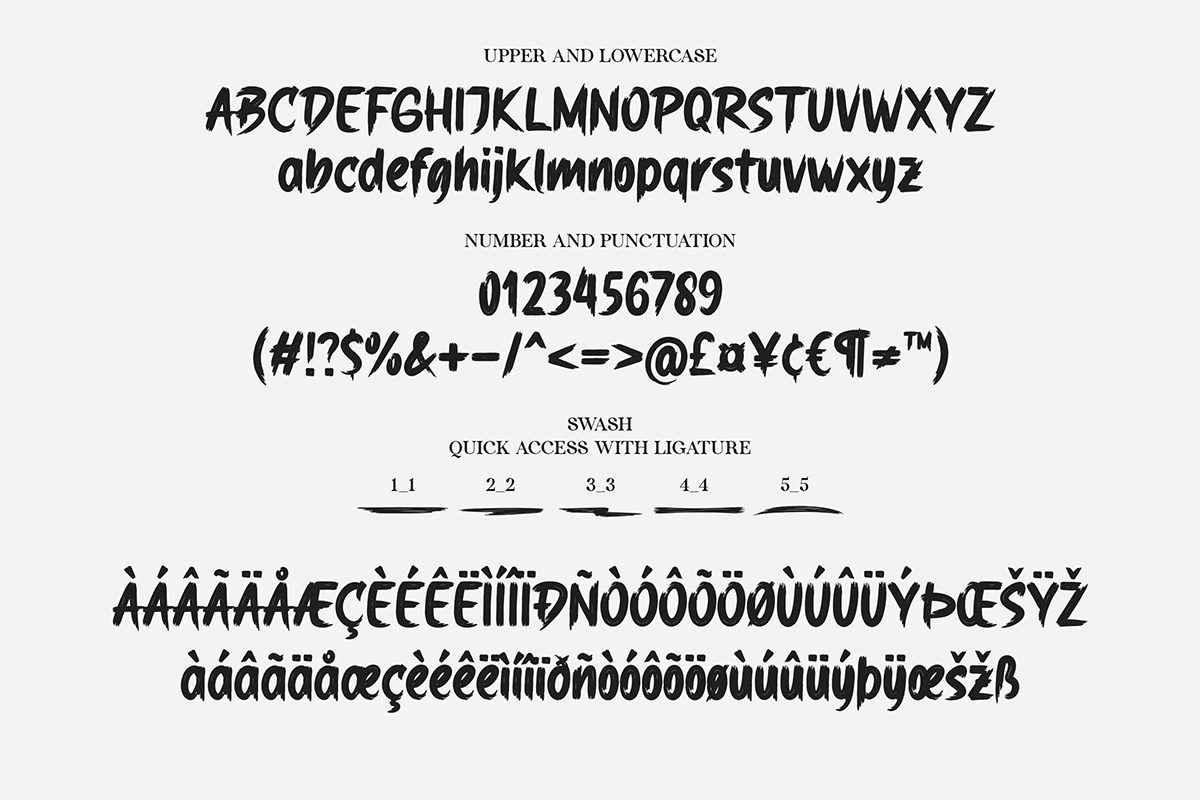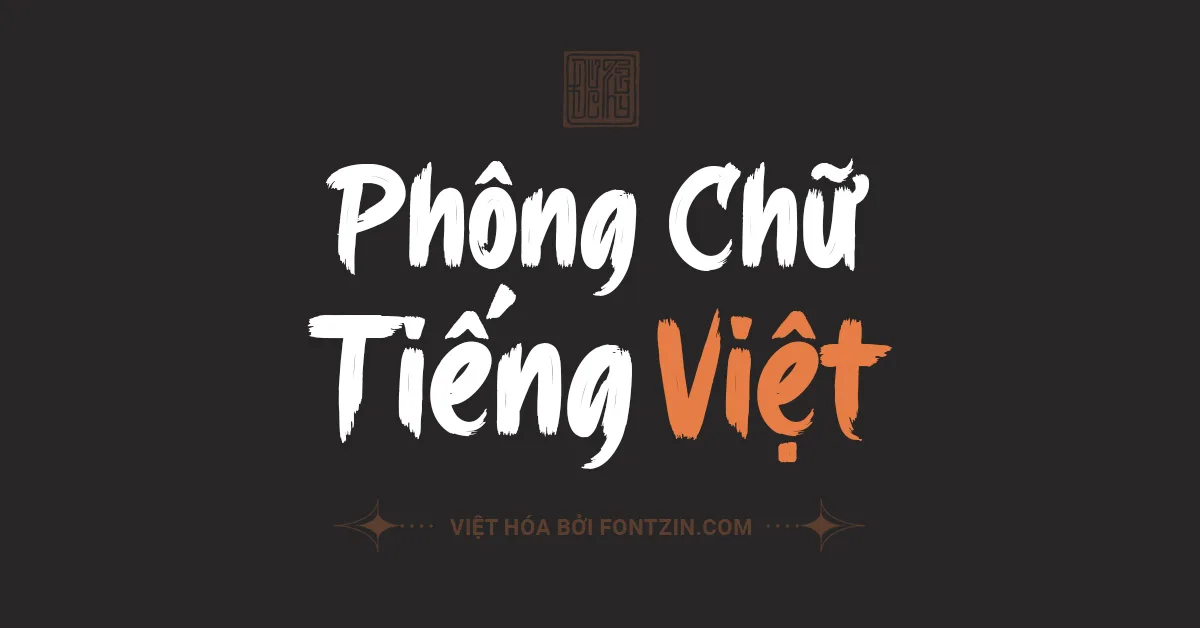
Tải Font Fz Donsky Việt Hóa
Tải Font Fz Donsky Việt Hóa: Phông chữ brush cá tính
Font FZ Donsky là một phông chữ nổi bật với phong cách cổ điển và ấn tượng, mang lại cảm giác mạnh mẽ và đầy cá tính. Với các đường nét thẳng tắp, đậm và góc cạnh, FZ Donsky là sự lựa chọn lý tưởng cho các thiết kế mang hơi hướng cổ điển, phong cách retro hoặc các dự án cần sự nổi bật. Phiên bản Việt hóa của font FZ Donsky đã được tinh chỉnh để phù hợp với các ký tự tiếng Việt, đảm bảo tính thẩm mỹ và đồng bộ khi sử dụng trong các thiết kế có ngôn ngữ tiếng Việt.
Font này phù hợp cho các ứng dụng trong tiêu đề, poster, bao bì sản phẩm hay những dự án sáng tạo cần sự nổi bật và cá tính. Nhờ sự Việt hóa đầy đủ, FZ Donsky giúp người dùng thoải mái sáng tạo mà không lo lắng về sự thiếu sót ký tự trong quá trình thiết kế.